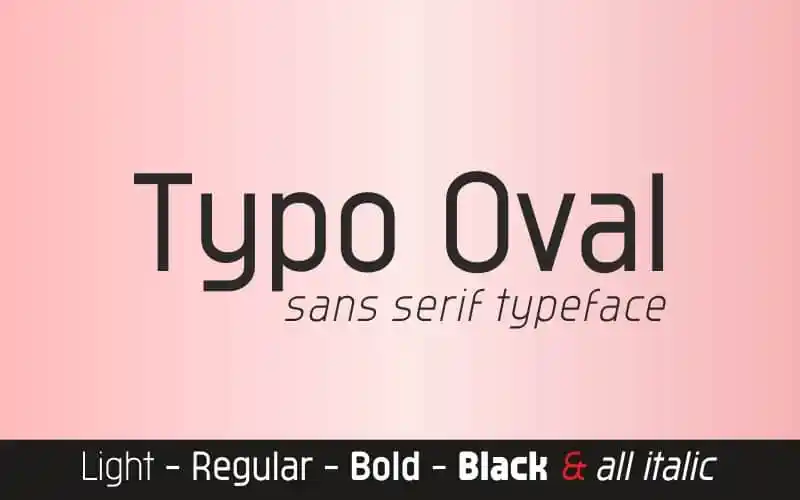
Typo Oval Sans Serif Font – Download Grátis
A Typo Oval Sans Serif é uma família de tipos elegante ou divertida dependendo do uso. Ela foi projetada pelo Studio Typo para designers que valorizam tanto a sofisticação quanto a versatilidade. Esta tipografia sans serif, luxuosamente agressiva em estilo, é perfeita para aplicação gráfica e uso na tela, seja para projetos como rótulos de marca, revistas, editoriais, cartas de noivado, desenho de logotipo, panfletos ou mídia social. Seja qual for o projeto que você está trabalhando em desenvolvimento, a Typo Oval Sans Serif tem uma atitude poderosa e um toque versátil capaz de dar vida a ele. Estou sempre pronta para transformar sua ideia digital em arte, seja ela tão formal quanto um logotipo ou tão descontraída como um convite de casamento. Experimente-a hoje!